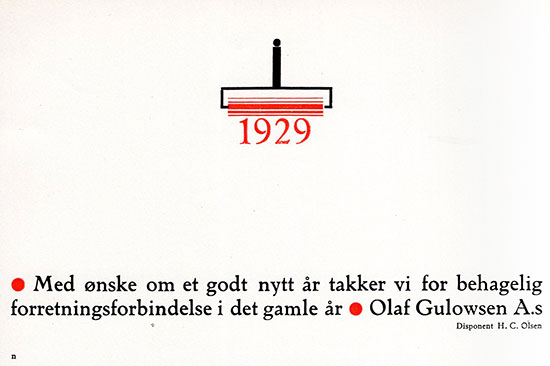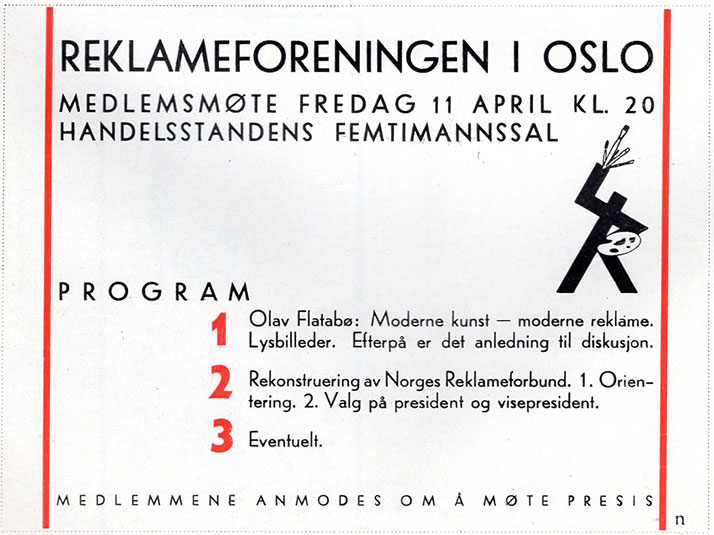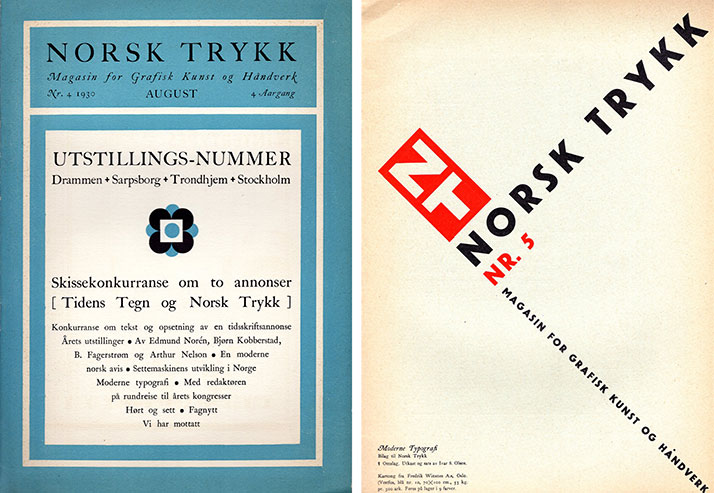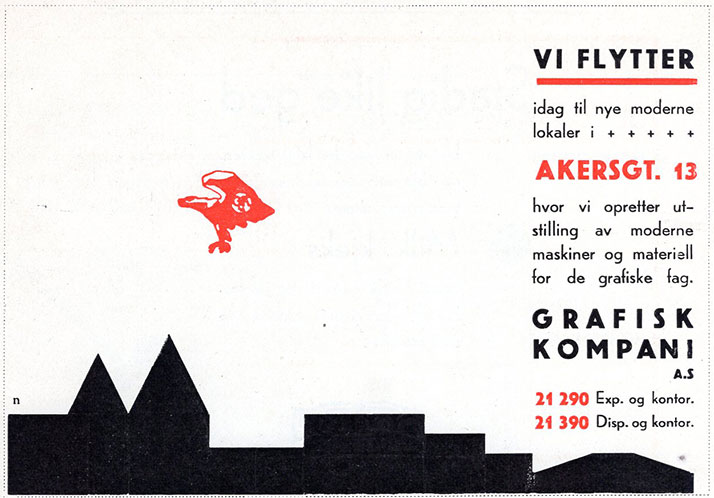
Med røtter i amerikansk klassisk typografi og reklame, ble Arthur Nelson den første talsmannen for «den nye typografien» i mellomkrigstidas Norge. Gjennom sitt tidsskrift Norsk Trykk formidlet han prinsippene for denne nye funksjonalistiske stilen.
Første del av denne artikkelen kartla hans vei fra læretid under den «frie retning» på slutten av 1800-tallet, til et mangeårig USA-opphold. Tilbake i Norge startet han et fagtidsskrift der han arbeidet for en klassisk typografisk stil. Hans typografi vakte motstand fra boktrykker Kirste, som ønsket en nasjonal stil i typografien.
Mens denne diskusjonen pågikk, vokste en annen stilretning – egentlig et helt nytt tankesett – fram, nemlig funksjonalismen. «Den nye typografien» – også kalt den «elementære» typografien – er funksjonalismen på det grafiske området.
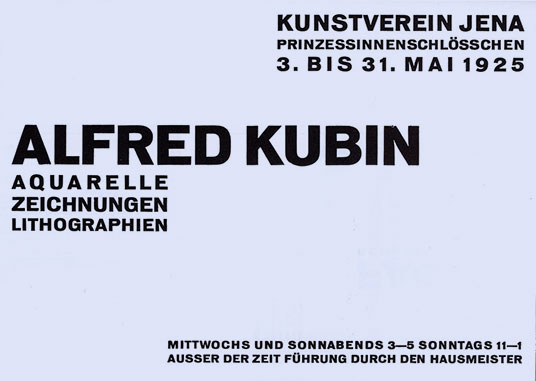
Eksempel på den nye typografiens asymmetri, bruk av grotesk skrift og utelatelse av ornamenter. Invitasjonskort formgitt av Walter Dexel, vist i Jan Tschicholds Die neue Typographie (1928). (Fargelagt av forfatteren i henhold til Tschicholds beskrivelse i boka.)
En ny typografi
Den nye typografien ville et brudd med den typografien som hittil hadde vært. Både nasjonale trekk og fortidige former skulle kastes over bord. Målet var effektiv kommunikasjon. Den nye typografien ville derfor det hensiktsmessige heller enn det vakre; den ville kontrast heller enn harmoni; den ville asymmetri i stedet for symmetri; den ville det objektive heller enn det personlige; den ville bruke groteske skrifttyper heller enn antikva, og den ville fjerne all unødvendig dekorasjon og kun tillate enkle geometriske ornamenter.
Den nye typografiens røtter lå i sovjetisk politisk kunst og i arbeidene til sosialistisk orienterte kunstnere og formgivere i vest, særlig i Tyskland.
Nelson kommenterte denne retningen første gang i Nelsons Magasin for Grafisk Kunst nr. 1, 1928 (dets andre utgave). Det er tydelig at han var blitt påvirket av den nye typografien. Hans eksempler på sin anbefalte moderne, norske typografi viser tekst bygget i blokk-stilen (alle linjer, også den siste, sluttet ut på samme bredde), og bruk av geometriske ornamenter. Men skriften var fortsatt Caslon.
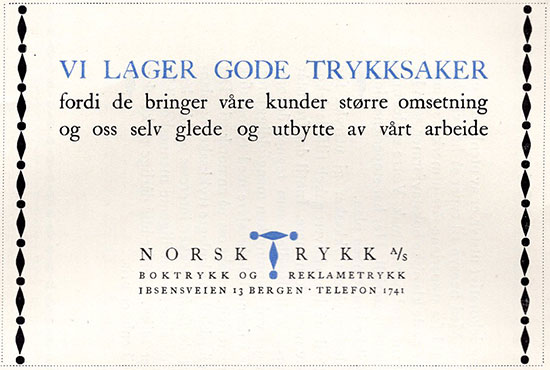
Arthur Nelsons eksempel på «Moderne Typografi» i Norsk Trykk nr. 1, 1928, er foreløpig langt fra den internasjonale modernismen, men han er tydelig påvirket.
Han sammenlignet sine mønstereksempler med den nye typografien: «Tyskerne har som bekjent i lengere tid arbeidet med et nyt typografisk system, ‘elementær typografi’, som også er basert på geometriske effekter, men de har efter min mening overdrevet systemet. Mens tyskerne gjennemfører blokk-systemet til også å omfatte skriften, idet de anvender grotesk, mener jeg at de vakre runde bokstaver egner sig bedre, særlig når der er meget tekst.»
Det var også en klar endring på magasinets form fra første til andre nummer: det var mindre av de gammeldagse formene, som de historiske avsnittstegnene og Caslon-ornamentene (se illustrasjon i forrige artikkel). Målet om en klassisk retning med amerikanske forbilder var forlatt. Nelsons geometriske ornamenter og blokkform var imidlertid en svært moderat tolkning av den nye typografien.
Det var naturlig at Nelson ble tiltrukket av den nye typografien. Han hadde bodd i New York, verdens mest moderne by. Han hadde på mange måter sett inn i framtida, og innsett at den ville bli vesentlig annerledes enn det han så rundt seg i Norge. Typografien måtte, som andre uttrykksformer, tilpasse seg den nye tida.
Konkurransen i næringslivet var blitt hardere, derfor fikk man reklamen, som hadde vokst fram som et stort arbeidsfelt. Dette måtte boktrykkerne kjempe for å få sin del av, mente Nelson. Boktrykkerne kunne derfor ikke bare være gode håndverkere; de måtte hjelpe kundene med planlegging og framsette forslag. Nelson gjorde seg til talsmann for planlegging gjennom skissering, og for tidsbesparende løsninger med et personlig, fikst moment. Han ville klare seg med én skriftfamilie i alle dens varianter, og noen slående effekter ved bruk av geometriske ornamenter.
Den nye typografien og den økende reklamen var som skapt for hverandre. Den nye typografien arbeidet for den direkte kommunikasjonen som også reklamen ville oppnå.
I det tyske fagtidsskriftet Typographische Mitteilungens spesialutgave «elementar typographie» (1925) ble det formulert ti punkter for den elementære typografien. Disse fokuserte blant annet på at den skulle oppfylle et formål gjennom meddelelse i «kortest og enklest mulig form og i mest mulig påtrengende form». (Disse punktene er publisert i norsk oversettelse her).
Slikt appellerte nok til reklamemannen Nelson. Han var dessuten på søken etter en stil i tråd med tidsånden, og fikk ferdig servert fra Tyskland en stil som nettopp påberopte seg å representere en ny tid. Men den sosialistiske tendensen som lå bak den nye typografien lå fjernt fra Nelson.
En geometrisk stil
Fra og med tredje nummer endret magasinet navn til Norsk Trykk. Gjennom 1928-årgangen ble den nye typografien omtalt flere ganger. Men det Nelson faktisk kategoriserte som sin anbefalte «moderne typografi» i hvert nummer, var lite mer enn en poengtert reklamestil. Han kalte sin stil geometrisk, fordi han brukte kun enkle geometriske ornamenter og formet teksten i blokker. Noen ganger bidro også kraftige streker til å skape et ytterligere blokkpreg. Arbeidene hans hadde nok også større kontraster enn det som var vanlig – Nelson ville et brudd med hva han kalte den «grå» typografi. Men hans arbeider var langt fra de radikale løsningene man så i Tyskland, og han distanserte seg fortsatt fra disse.
This is part two of two articles about the Norwegian printer Arthur Nelson. His trade magazine Norsk Trykk was instrumental in spreading the ideas of the modernist «new typography» in Norway. Slowly and modestly he accepted it and started practicing it, as well as commenting on it and giving talks about it. But he never left the traditional Caslon-based typography, which he had met while working for 20 years in USA.
Arthur Nelson (1878–1957), født Nielsen. Bildet er trolig fra 1930-tallet.